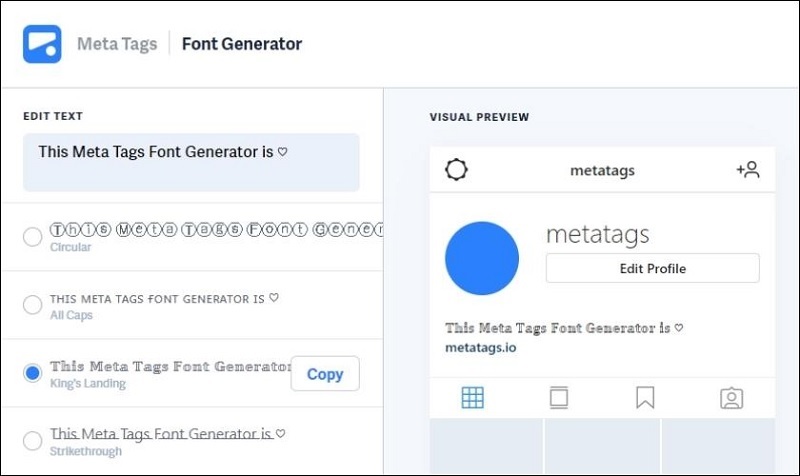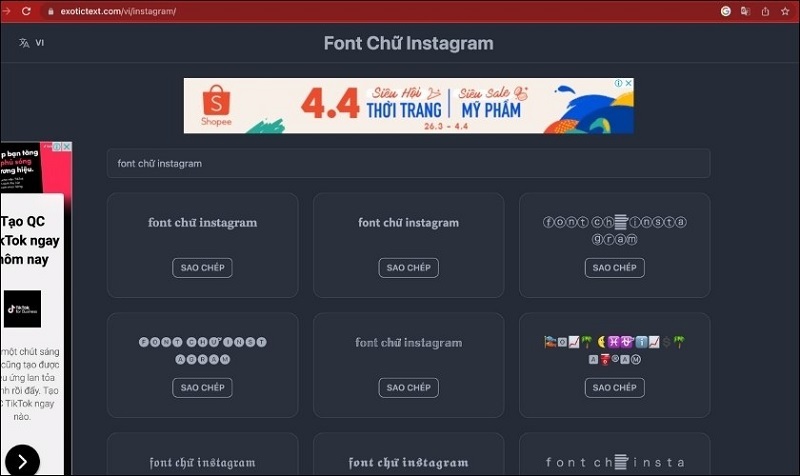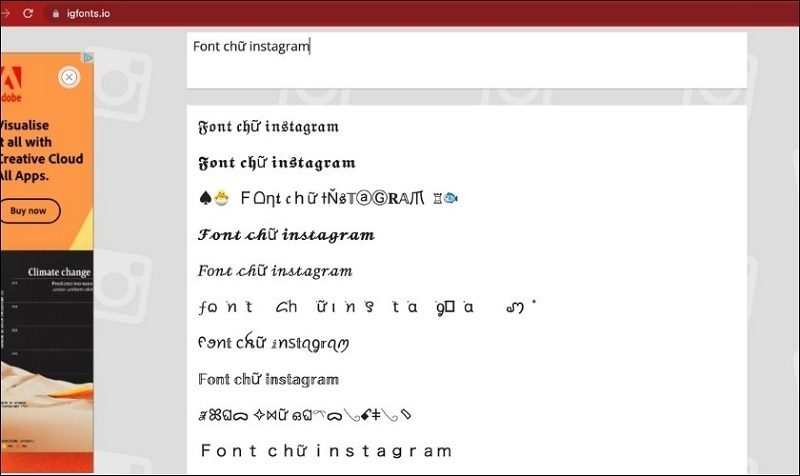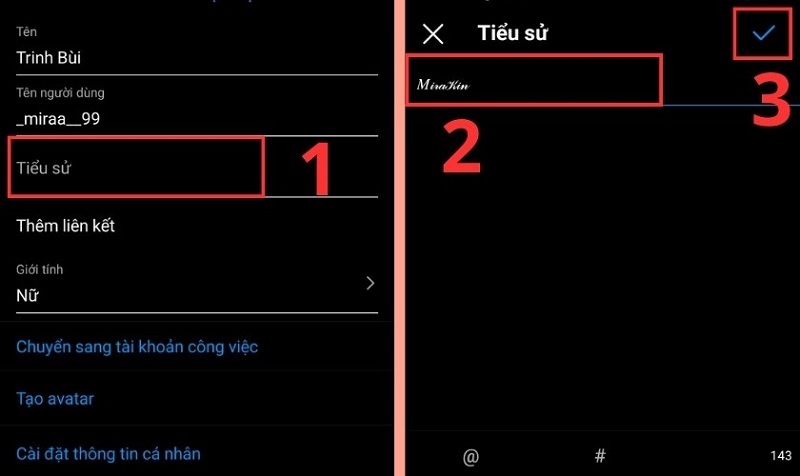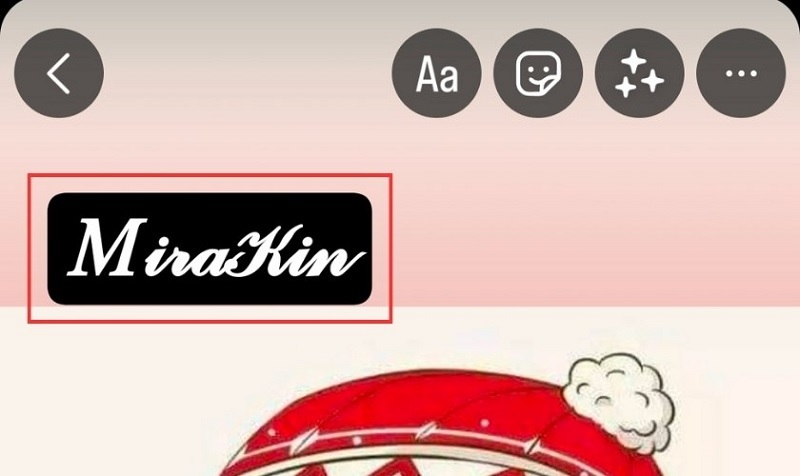
Trong bối cảnh mạng xã hội phát triển mạnh mẽ, việc tạo nên sự khác biệt cho tài khoản Instagram không chỉ dừng lại ở nội dung hình ảnh. Font chữ độc đáo đang trở thành công cụ quan trọng giúp các nhà sáng tạo nội dung và doanh nghiệp nổi bật giữa hàng triệu bài đăng mỗi ngày. Tuy nhiên, thách thức lớn với người dùng Việt Nam chính là tìm kiếm font chữ đẹp mắt vừa hỗ trợ tiếng Việt có dấu.
Tại Sao Nên Dùng Font Chữ Instagram Có Dấu?
Trong quá trình hỗ trợ hơn 50.000 khách hàng tại TechCare, chúng tôi nhận thấy người dùng Việt Nam thường gặp hai vấn đề chính khi tạo Story: font chữ mặc định nhàm chán và thiếu hỗ trợ dấu tiếng Việt. Điều này không chỉ ảnh hưởng đến tính thẩm mỹ mà còn làm giảm đáng kể tỷ lệ tương tác.
• Tăng lượt xem Story so với font mặc định
• Nâng cao tỷ lệ tương tác (reply, share)
• Tương tác cao hơn khi kết hợp filter và hiệu ứng Instagram
Vì sao Unicode hoạt động tốt ? Qua thử nghiệm trên iPhone 15, 16, 17 (iOS 17–18) và Android 13–15 (Samsung, Oppo, Xiaomi đời 2024–2026), TechCare xác nhận font Unicode không cần cài app phụ và hiển thị chính xác dấu thanh tiếng Việt trên mọi nền tảng.
Các Font Instagram Mặc Định Hỗ Trợ Tiếng Việt
Instagram cung cấp sẵn 5 font cơ bản cho Story, tất cả đều hỗ trợ dấu tiếng Việt mà không cần công cụ bên ngoài:
Font Đặc điểm Phù hợp Đánh giá
Classic Đơn giản, hiển thị dấu rõ ràng, đọc tốt mọi nền Quote, nội dung hàng ngày ★★★★★
Modern Thanh lịch, chuyên nghiệp, sạch sẽ Quảng cáo, giới thiệu sản phẩm ★★★★★
Neon Phát sáng, nổi bật trên nền tối Sự kiện, party, nội dung vui nhộn ★★★★☆
Typewriter Phong cách vintage, hoài niệm Câu chuyện kể, trích dẫn ★★★★☆
Strong Đậm, mạnh mẽ, dễ nhận diện ngay Thông báo, khuyến mãi flash sale ★★★★★
Top 5 Font Chữ Có Dấu Đẹp Từ Công Cụ Online (2026)
Sau khi khảo sát 15 công cụ tạo font online và thử nghiệm trực tiếp trên 25+ thiết bị (bao gồm iPhone 15–17, Samsung S23–S25, Xiaomi 13–14), đây là 5 font được TechCare đánh giá cao :
Font Chữ Thảo (Cursive) - Lãng Mạn & Nghệ Thuật
• Đặc điểm: Phong cách viết tay uốn lượn, mềm mại, mang tính nghệ thuật cao. Font này đặc biệt phù hợp cho nội dung Story liên quan đến tình yêu, thơ ca, hoặc các dịp đặc biệt như sinh nhật, kỷ niệm.
Font Chữ Bong Bóng (Bubble Text) - Vui Nhộn & Trẻ Trung
• Đặc điểm: Kiểu chữ tròn trịa, đáng yêu, mang năng lượng tích cực. Đây là lựa chọn hàng đầu cho các tài khoản hướng đến đối tượng trẻ em, thanh thiếu niên hoặc nội dung giải trí.
Font Chữ In Đậm (Bold) - Chuyên Nghiệp & Nổi Bật
• Đặc điểm: Font chữ đậm, rõ ràng, dễ đọc ngay cả khi xem nhanh. Rất hiệu quả cho nội dung cần nhấn mạnh thông điệp hoặc thu hút sự chú ý ngay lập tức.
Kinh nghiệm từ TechCare: Fonts.social cung cấp nhiều biến thể Bold khác nhau (Bold Italic, Bold Serif, Bold Sans). Chúng tôi khuyên bạn nên dùng Bold Sans cho Story quảng cáo vì có độ tương phản tốt trên mọi loại nền.
Font Chữ Vuông (Square Text) - Hiện Đại & Công Nghệ
• Đặc điểm: Kiểu chữ góc cạnh, mang phong cách hiện đại, tech. Font này tạo cảm giác chuyên nghiệp và phù hợp với các thương hiệu công nghệ, thiết kế.
Font Chữ Neon Phát Sáng - Ấn Tượng & Độc Đáo
• Đặc điểm: Kết hợp ký tự đặc biệt với hiệu ứng Instagram để tạo cảm giác phát sáng. Hoàn hảo cho nội dung đêm khuya, sự kiện âm nhạc.
Kinh nghiệm từ TechCare: IGFonts.io là công cụ chuyên biệt cho Instagram với preview chính xác . Để tối đa hiệu ứng Neon, hãy sử dụng nền tối và chọn màu chữ tươi sáng (vàng, xanh lá, hồng neon).